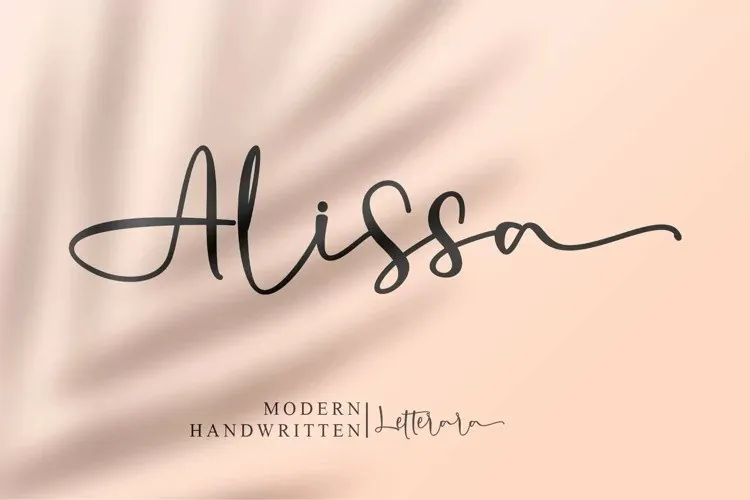
Alissa Font – Fonte Grátis
Alissa Font – Download Grátis
Alissa Font
A fonte ‘Alissa Font’ é uma elegante tipografia feminina projetada pelo Thomas Aradea, adequada para adicionar um toque sofisticado a seus designs gráficos. Este script curvilíneo se destaca por seu charme e graça nos traços e juntas de letras chamadas ‘swashes’, tornando-o perfeito para variados usos como logotipos, identidades corporativas, convites, embalagens, cartas pessoais, cards de eventos e posts nas redes sociais. Além disso, a fonte é PUA (Proprietary Unicode Attributes) codificada, facilitando o acesso a todas as características deliciosamente criativas do tipo para uma experiência de uso fluida e intuitiva. Possui várias opções alternativas de traços e juntas ligadas que oferecem flexibilidade e personalização extra aos designers. Alissa é um recurso valioso tanto para iniciantes quanto para profissionais, ideal para aqueles buscando uma fonte moderna com um toque clássico.